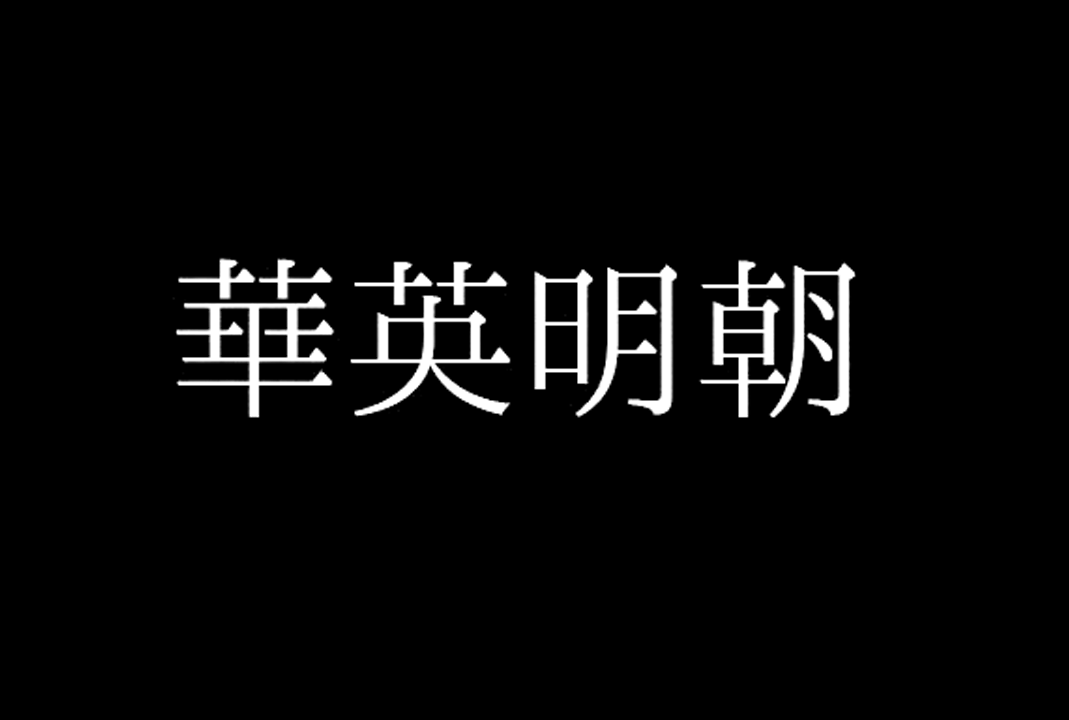
Huaying Mincho 华英明朝(華英明朝)是一套拥有传承字形、旧字形风格的中文字体。华英明朝共提供 3 种字形风格。
HuayingMincho.ttc华英明朝-旧印体TTC旧印刷体,字形接近新细明体(旧版)。
HuayingMinchoOld.ttf华英明朝-旧印体TTF旧印刷体,字形接近新细明体(旧版)。
HuayingMinchoClassic.ttf华英明朝-传承体 TTF传承字形,字形部件较为统一。
HuayingMinchoODict.ttf 华英明朝-旧典体 TTF接近《康熙字典》中的字形,字形部件不统一。
HuayingMinchoT.ttf 華英明朝-繁體 TTF由传承体修改,可实现简入繁出的字体。